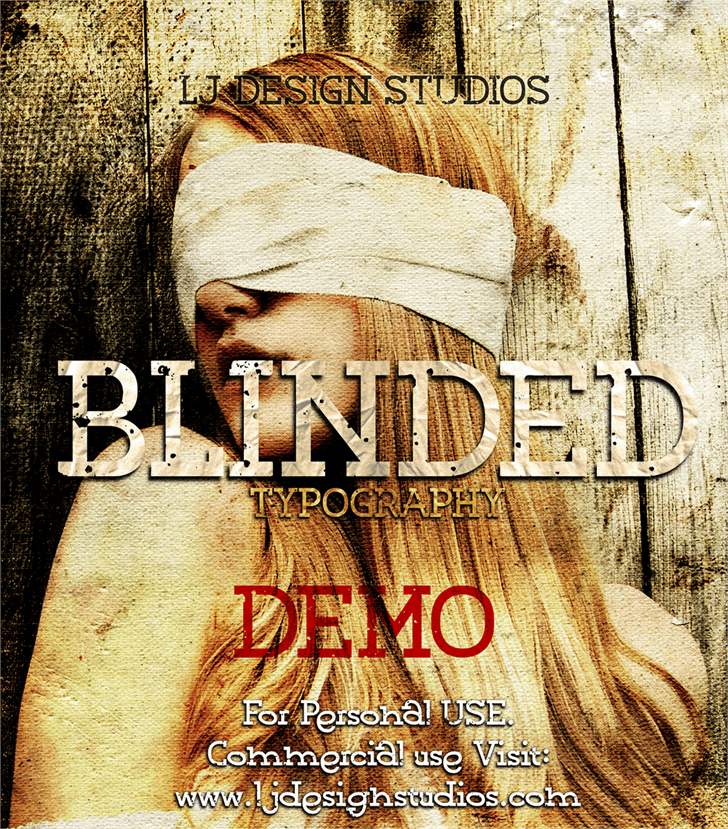
A Blinded Font é uma escolha perfeita para designers buscam algo mais que a simplicidade dos serifos tradicionais. Esta slab serif traz uma identidade visual interessante e atemporal, com linhas marcantes que criam um contraste dinâmico em qualquer projeto. O nome Hamilton foi o responsável pelo design desta fonte, oferecendo letras, números e símbolos num estilo clássico moderno. Ideal para uso comercial sem custos adicionais, a Blinded Font mantém sua simplicidade com elementos de forma direta e formas fechadas que se destacam. Seja em aplicações de design editorial ou branding digital, esta fonte traz um toque único e moderno ao seu trabalho. Com uma presença sólida nas redes sociais – Facebook, Twitter, Instagram e Behance – Hamilton não hesita em compartilhar sua visão criativa com o público. Com a Blinded Font, você encontra uma solução elegante para qualquer necessidade de texto que exija um toque visual distintivo. Seja uma marca, um design editorial ou até mesmo um layout web responsivo, esta fonte vai trazer seu trabalho para frente e acima dos demais com sua característica aparentemente simples mas repleta de expressividade.